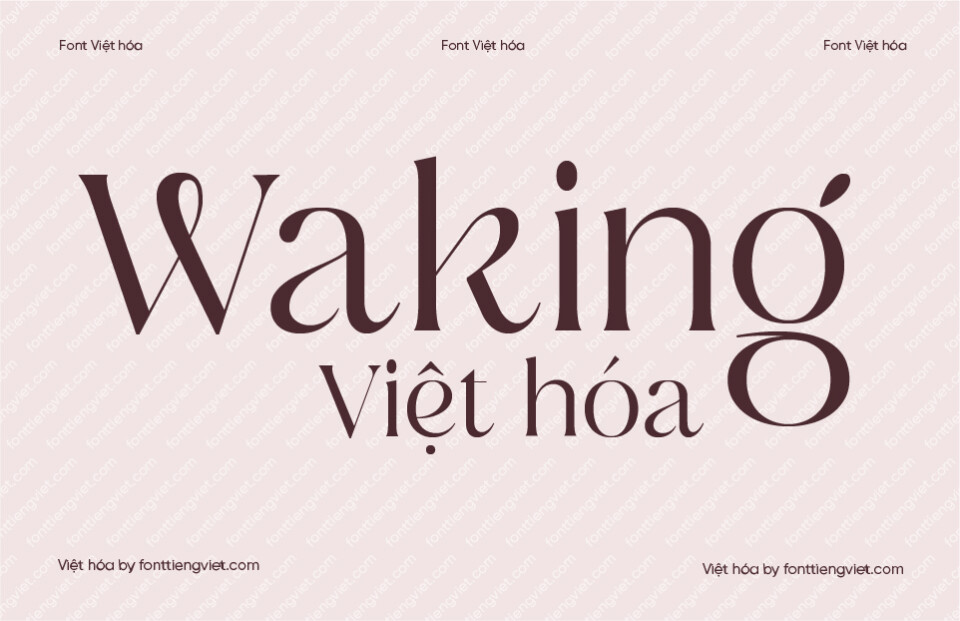
Font Việt hóa 1FTV VIP Waking
Giới thiệu về Font Việt hóa 1FTV VIP Waking
Trong thế giới đồ họa hiện đại, việc tìm kiếm một bộ Font Miễn Phí chất lượng và hỗ trợ đầy đủ tiếng Việt luôn là ưu tiên hàng đầu của các nhà thiết kế. Font Việt hóa 1FTV VIP Waking nổi lên như một sự lựa chọn hoàn hảo nhờ phong cách thiết kế độc đáo và hiện đại. Đây là bộ font mang hơi hướng tự do, phóng khoáng nhưng vẫn giữ được nét tinh tế cần thiết cho các ấn phẩm chuyên nghiệp. Khi sử dụng 1FTV VIP Waking, người dùng sẽ cảm nhận được sự tỉ mỉ trong từng đường nét, giúp các thông điệp truyền tải trở nên sống động và thu hút thị giác hơn bao giờ hết.
Đặc điểm nổi bật của Font Việt hóa 1FTV VIP Waking
Phong cách thiết kế hiện đại và trẻ trung
Bộ Font Việt hóa 1FTV VIP Waking sở hữu cấu trúc chữ cái thanh thoát với các nét uốn lượn tự nhiên. Điều này tạo nên cảm giác thân thiện và gần gũi, rất phù hợp cho các dự án liên quan đến giới trẻ, giáo dục hoặc quảng bá sản phẩm sáng tạo. Các ký tự được chăm chút kỹ lưỡng để đảm bảo tính thẩm mỹ cao nhất khi hiển thị trên cả màn hình kỹ thuật số lẫn bản in truyền thống.
Khả năng hiển thị tiếng Việt hoàn hảo
Một trong những điểm mạnh nhất của Font Việt hóa 1FTV VIP Waking chính là bộ dấu tiếng Việt được tinh chỉnh tối ưu. Các lỗi thường gặp như dấu bị lệch, kích thước dấu không đồng nhất hay ký tự bị lỗi hiển thị đã được khắc phục hoàn toàn. Điều này giúp các thầy cô giáo, học sinh và các bạn thiết kế có thể yên tâm sử dụng trong các bài giảng, báo cáo hay banner mà không lo ngại về vấn đề lỗi kỹ thuật font chữ.
Ứng dụng thực tế của Font Việt hóa 1FTV VIP Waking
Thiết kế banner và poster sự kiện
Nhờ vẻ ngoài ấn tượng, 1FTV VIP Waking thường được ưu tiên dùng cho các tiêu đề lớn trên poster, banner quảng cáo. Sự phá cách trong hình khối của chữ giúp tiêu đề trở nên nổi bật giữa các thành phần đồ họa khác, tạo điểm nhấn mạnh mẽ cho người xem ngay từ cái nhìn đầu tiên.
Trang trí tài liệu học tập và giảng dạy
Đối với môi trường học đường, bộ font này mang lại sự tươi mới cho các bài thuyết trình PowerPoint hoặc các tập tài liệu bổ trợ. Thay vì sử dụng những font chữ mặc định khô khan, việc áp dụng 1FTV VIP Waking sẽ giúp nội dung trở nên hấp dẫn hơn, kích thích sự hứng thú học tập của học sinh. Sự rõ ràng của các ký tự cũng giúp việc đọc văn bản trở nên dễ dàng và thuận tiện.
Kết luận về bộ font độc đáo này
Với sự kết hợp giữa tính nghệ thuật và sự tiện dụng, Font Việt hóa 1FTV VIP Waking xứng đáng là một công cụ không thể thiếu trong kho tài nguyên của bất kỳ ai yêu thích cái đẹp. Bộ font này không chỉ giúp nâng tầm giá trị cho các bản thiết kế mà còn thể hiện phong cách cá nhân riêng biệt của người sử dụng. Nếu bạn đang tìm kiếm giải pháp tối ưu cho dự án tiếp theo, hãy trải nghiệm ngay Font Miễn Phí, Font Việt Hóa, Font Việt hóa 1FTV VIP Waking để thấy được sự khác biệt vượt trội mà nó mang lại cho công việc của bạn.